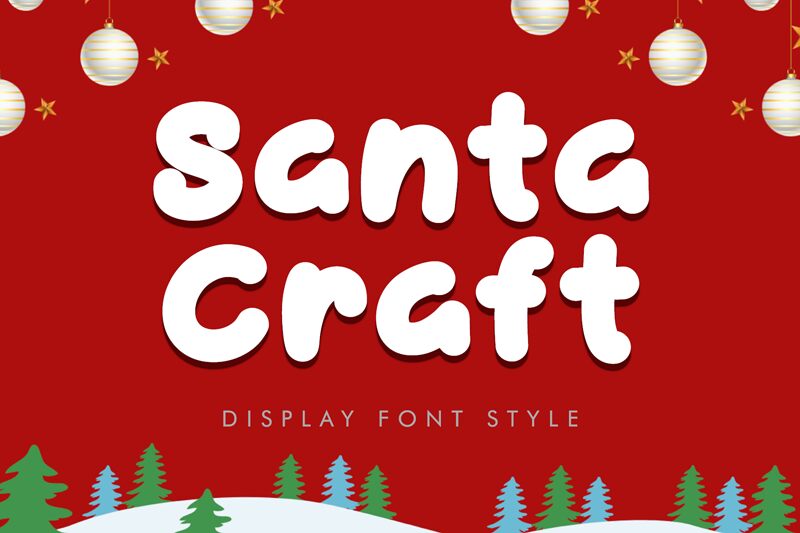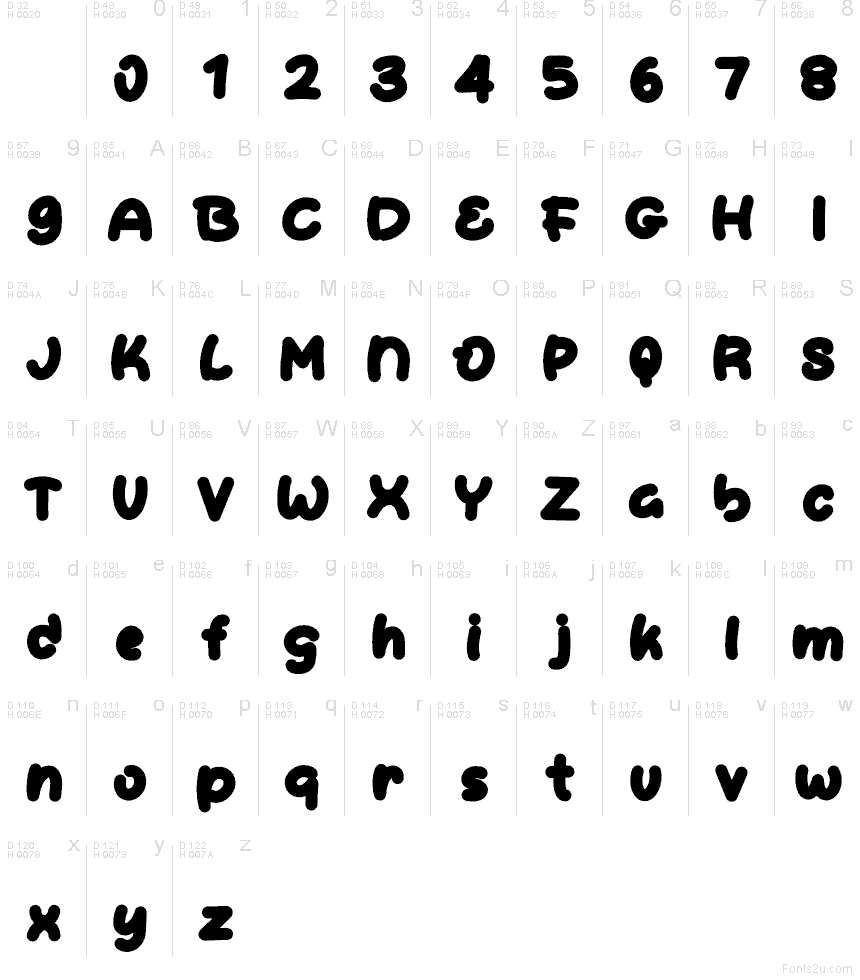
Santa Craft Demo
Santa Craft - это мультяшный дисплейный шрифт с округлыми, полными формами и мягкими изгибами, которые придают буквам дружелюбный, «ручной» ритм. Простые и плавные линии делают его идеальным для создания радостного праздничного настроения или оформления хендмейд-проектов.
Santa Craft отлично подходит для рождественских открыток, сезонных постеров, бирок для изделий ручной работы, приглашений и брендинга - его мягкие, непринужденные формы создают ощущение тепла. Это отличный выбор для наклеек и декоративных заголовков, когда вы хотите, чтобы надпись выглядела празднично и располагающе.